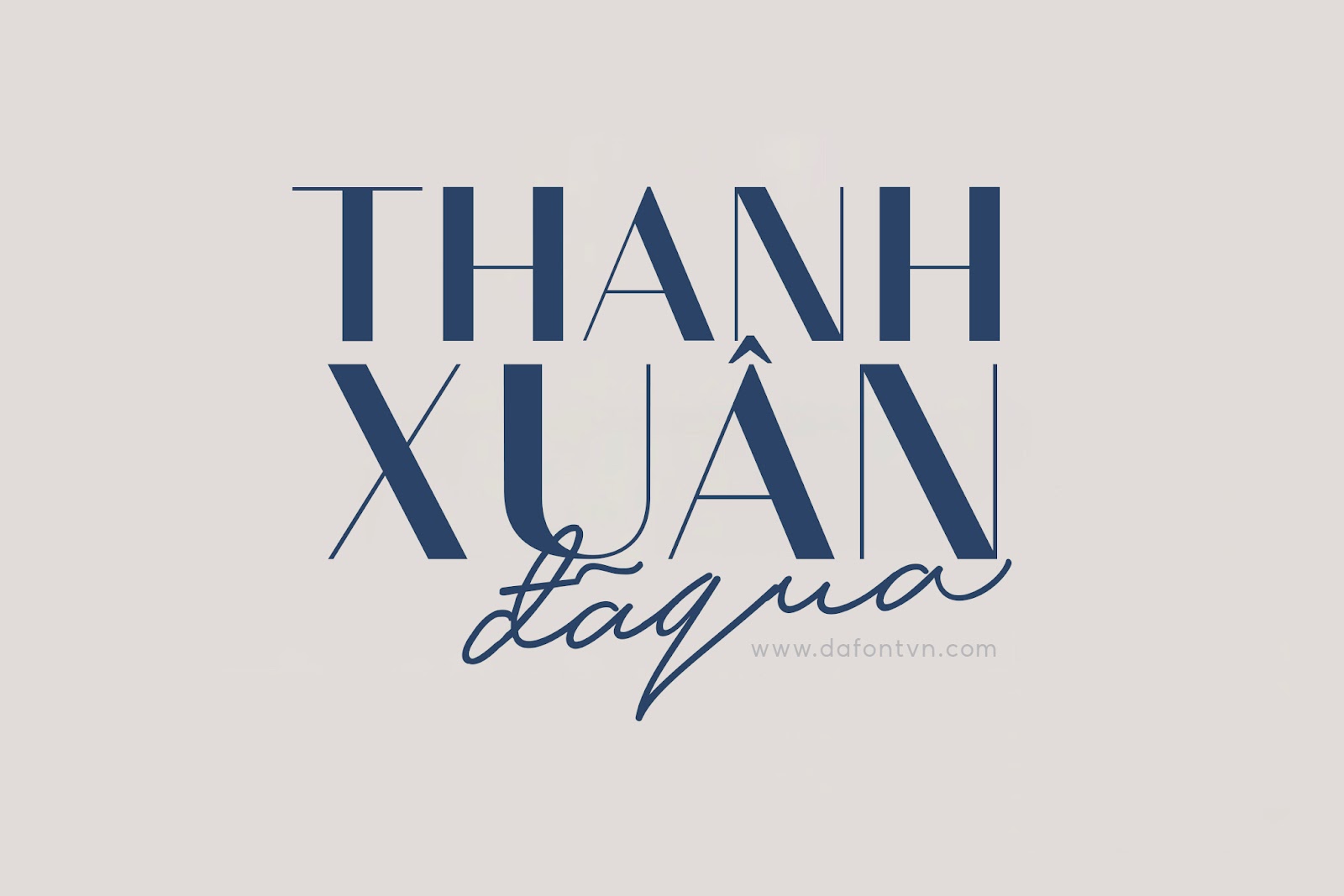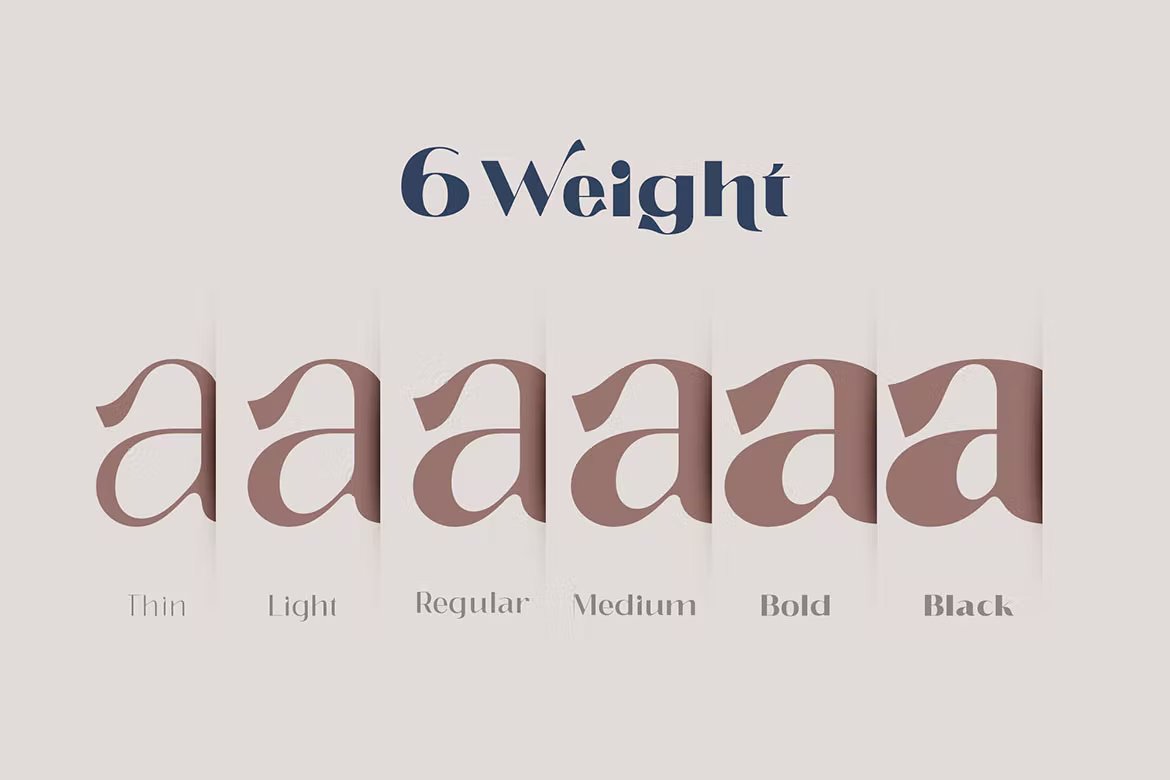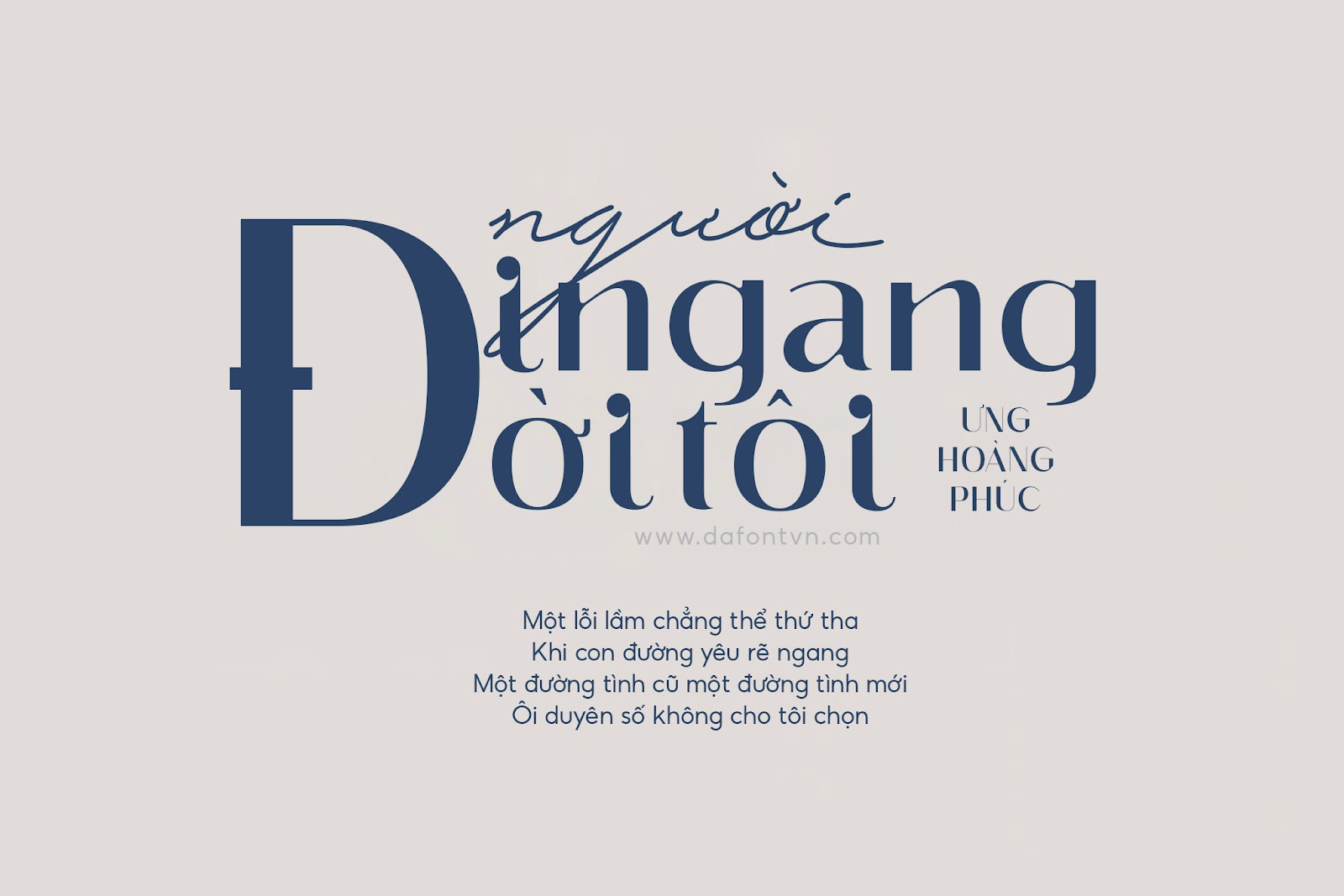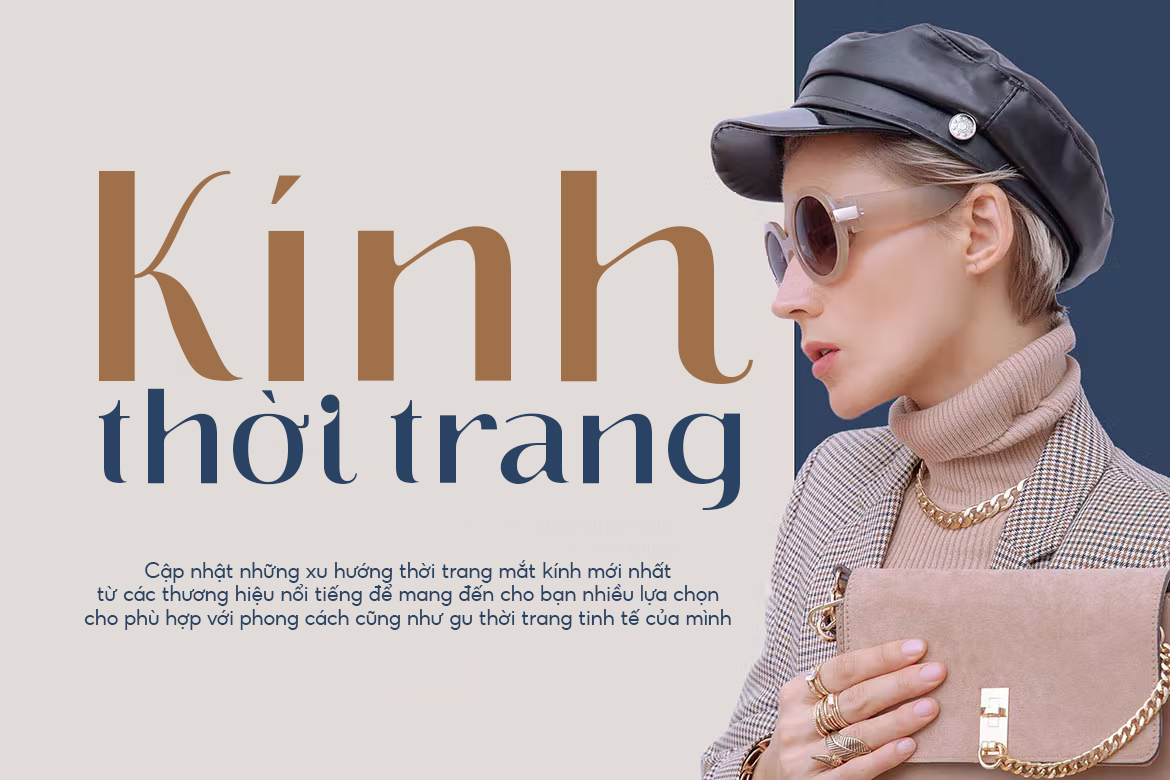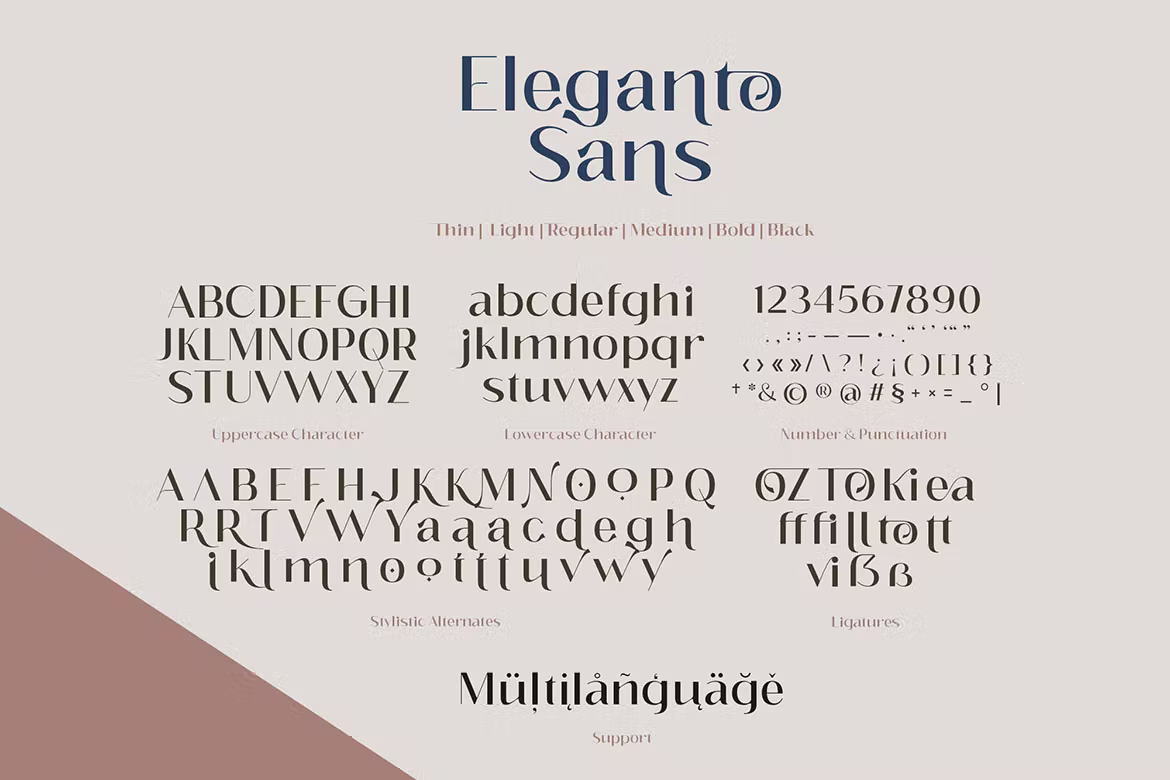
Font Việt hóa Eleganto Sans (6 font)
Eleganto Sans font hiện đại hợp thời trang với các chữ thay thế đặc biệt, được thiết kế các đường nét quyến rũ và gợi cảm phù hợp cho hầu hết các thiết kế như xây dựng thương hiệu, tạp chí, thời trang, nhà hàng,…
Bao gồm 6 kiểu: